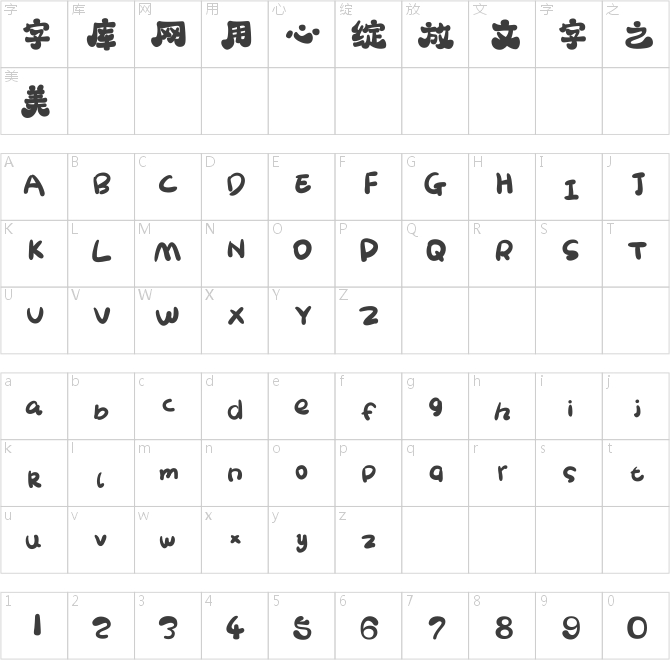
字體名稱: 點(diǎn)字QQ糖
點(diǎn)字QQ糖
點(diǎn)字QQ糖字體字庫(kù)是一款讓人賞心悅目、百看不厭的中文字體,適合各類廣告和產(chǎn)品包裝設(shè)計(jì)應(yīng)用,字體大小4.63MB,格式為ttf字體,上傳用戶是程玉玲,作者/版權(quán)方為點(diǎn)字庫(kù)